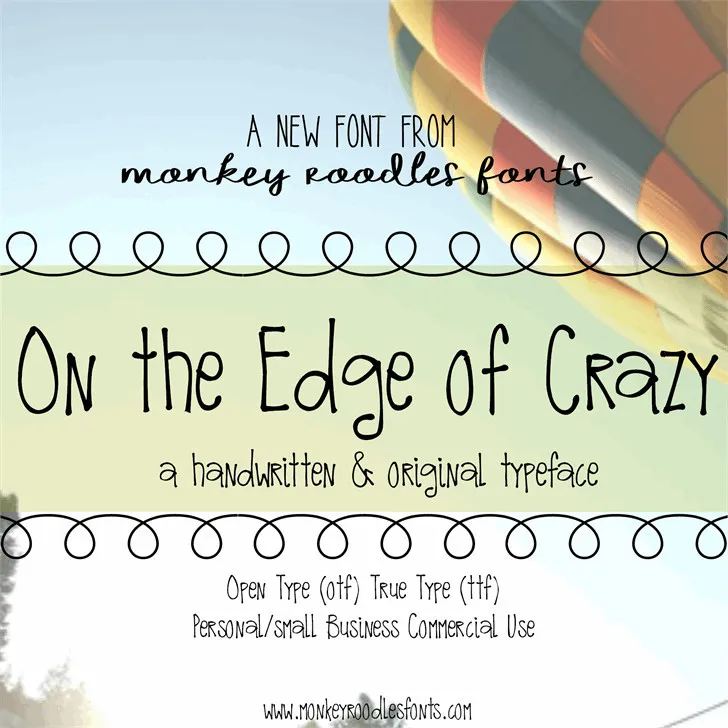
Descubra a essência do design autêntico com MRF On the Edge of Crazy Font. Confeccionada pela habilidosa mão de Hamilton, esta fonte livre para uso pessoal oferece um touch único e desenho autoral que traz à vida textos de forma encantadora. Sujeitosa e emocionalmente próxima, ela transmite uma onda de energia vibrante e originalidade sem igual. Ideal tanto para designers profissionais quanto para entusiastas da arte digital, MRF On the Edge of Crazy Font é um acréscimo inestimável ao seu conjunto de ferramentas de design. Embora seja fornecida gratuitamente para uso pessoal, não hesite em explorar as opções de licenciamento comercial para integrá-la com sua própria identidade visual e promover suas ideias criativas com mais ênfase. Visite Monkey Roodles Fonts (www.monkeyroodlesfonts.com) para obter mais informações sobre MRF On the Edge of Crazy Font, uma verdadeira jóia no mundo de fontes manuscritas. Em busca da sua próxima inspiração? Descubra a beleza nas linhas e na forma com Hamilton’s MRF On the Edge of Crazy Font.